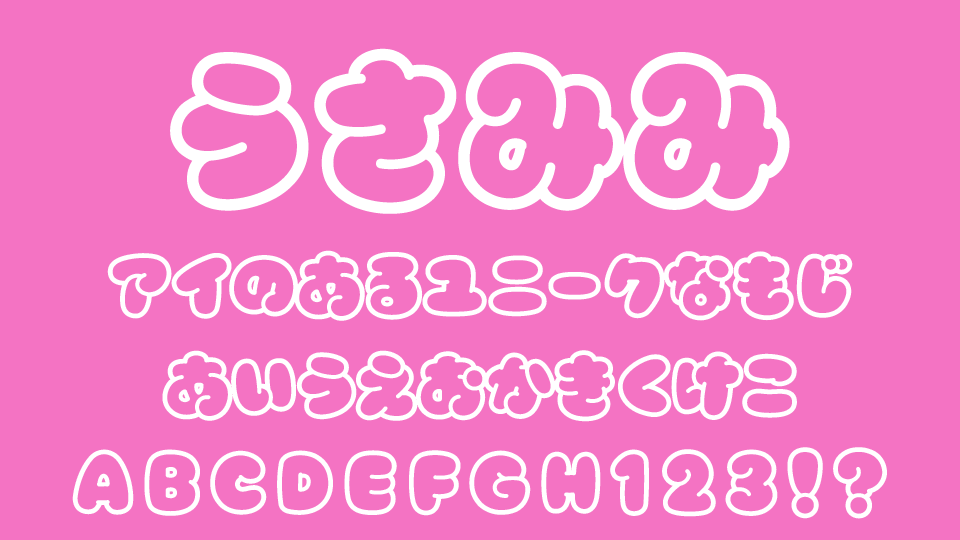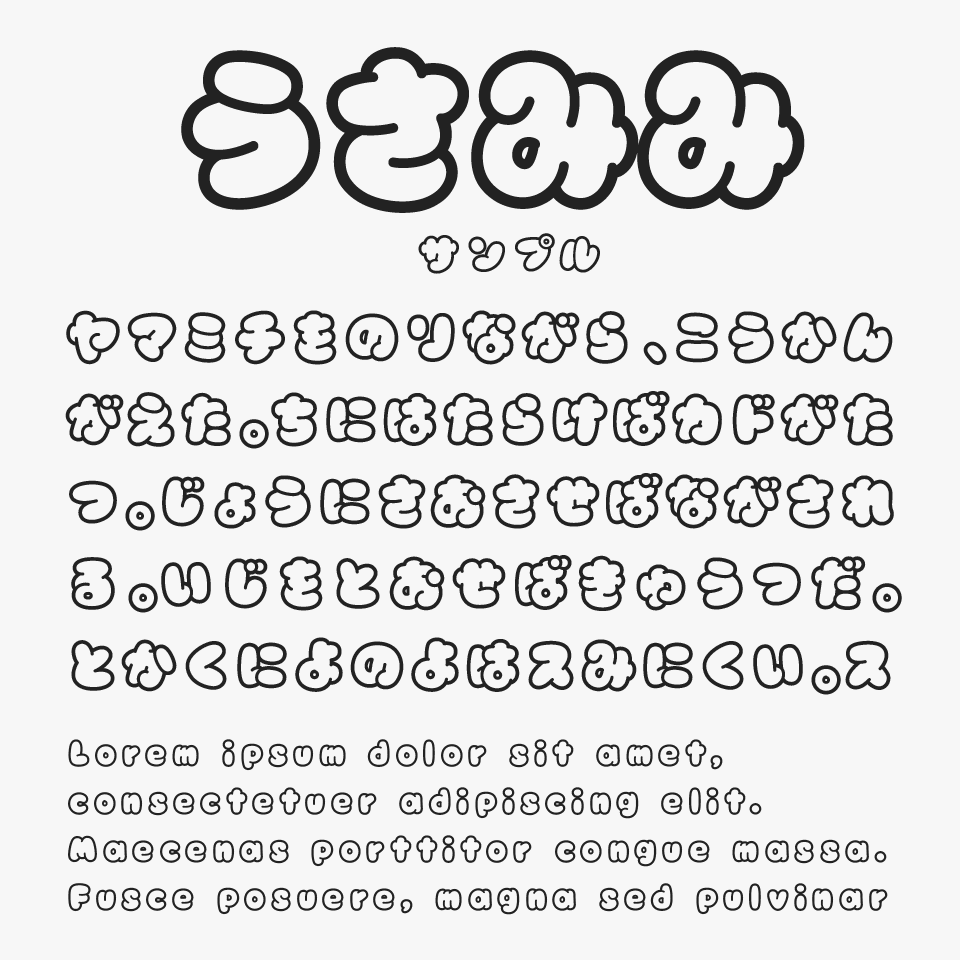
うさみみ
うさみみフォントは、文字の輪郭にうさぎの耳や丸いしっぽを思わせるふくらみを取り入れた、ふわふわと可愛らしいデザインフォントです。
太めのアウトラインと丸みを持たせたシルエットによって、文字そのものが小さなキャラクターのように見えるのが特徴です。ひらがなだけでなく英字にも同じモチーフが取り入れられており、文章全体を統一感のある可愛らしい雰囲気をつくることができるフォントです。
うさぎをテーマにしたグッズや子ども向けコンテンツ、お菓子のパッケージ、推し活、SNS投稿、イベントPOPなど、可愛らしさをしっかり打ち出したいデザインにぴったりなフォントです。丸みのある形が多いため、パステルカラーやイラストとも合わせやすく、ふんわり甘い世界観によく似合うフォントです。
収録文字は、ひらがな・カタカナ・アルファベット・数字・記号が収録されています。